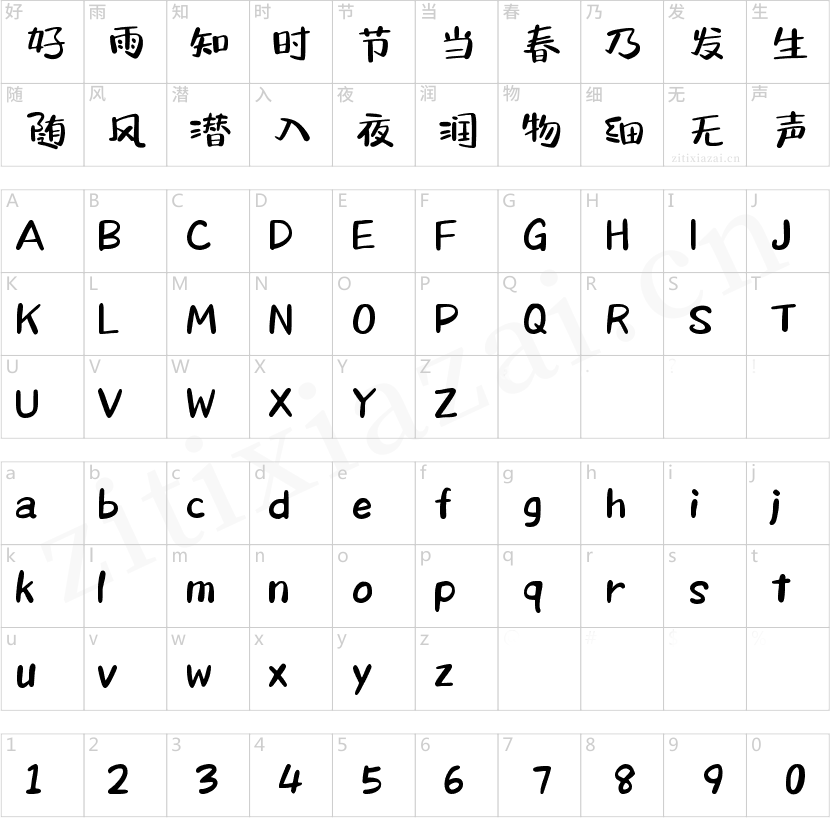
Aa荷包鼓鼓
Aa荷包鼓鼓,这款字体结构工整、笔画清晰,兼顾美观与易读性,适用于标题、正文、海报、包装、LOGO 等多种场景。字形优雅稳定,风格百搭耐看,适配日常排版与创意设计,让文字呈现更舒适、更具质感。Aa荷包鼓鼓一笔一画,皆是细节,以均衡的比例、流畅的线条打造舒适视觉体验,字形端正大气,风格简约现代。无论是商业设计、品牌宣传还是日常排版,都能轻松驾驭,让文字更有格调与力量。Aa荷包鼓鼓字体下载。
Aa荷包鼓鼓字体
Aa荷包鼓鼓是一款非常具有艺术性的字体,它的设计灵感来源于对古典艺术的研究,同时又融入了现代字体设计的元素。字形优美,笔画粗细变化自然,给人以大气、典雅的感觉。Aa荷包鼓鼓是一款既传统又现代的字体,它的设计充满艺术感,美观大方,实用性也非常强。无论是对于设计师还是对于普通读者来说,都是一种非常不错的字体选择。Aa荷包鼓鼓适合用于具有艺术感的场合,比如海报、宣传单张、书籍封面等。由于其字形流畅且具有动态感,也适合用于大量的文本排版,如报纸、杂志等。